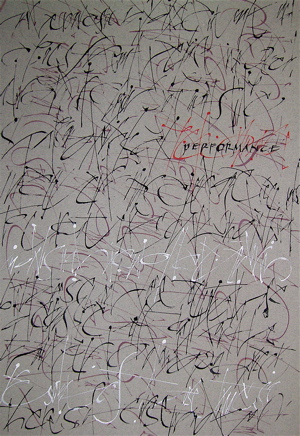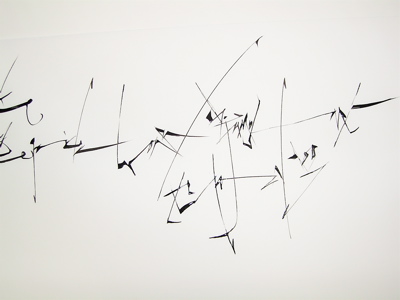
ポリリズミック
先週末に来日中のデニス(デニオとも言う)ブラウン氏のワークショップを受講しました。
タイトルは「ポリリズミック」!
いくつものリズムが入っている文字を求めて今日も書く、明日も書く、あさっても書くのです。
右脳と左脳から出た信号が手に流れて、自然と美しい文字や線が即興的に直感的に生まれてくる様に、ひたすら書く。ペンを意識的に「コントロール」するのではないのです。Let them go!
あんなラインできないわ〜、デニ男じゃないからムリ〜、と逃げるのは簡単です。・・・が、ここであきらめてはいけまへん。あきらめたら女がすたるっ!?
だって、あきらめたらこれより先にはいつまでたっても進めないし、進めたらもっと先が見えて来るかもしれないのです〜。あ〜、でも大変!
そういう気持ちにさせるデニ男さんはやはり一流のカリグラファーなんですね。いやはや、すごいザンス!
ワタシ的にはとっても受けました。
Sさんのポリリズム、ステキですー。スキスキっ。
興奮していますっ。私ー。
今回のWSではベテラン様揃いなので、イタリック以外のものも期待していました。すばらしいです!!!
書けば書くほど燃えてきますよね。私も燃えています。。デニ男は「デニオ」という響き、好きみたいです。
確かに、本当にその気になっている私、彼の才能、パワーのおかげです。やっぱりすごいですね。
ikukoさんのポリリズミックも是非是非発展させて、いつか必ず拝見させて下さいね。楽しみにしていますっ!燃えてくださいっ!
ゴッちゃんにディアンコ、そして”デニ男”だなんて、カリグラフィー界の巨匠達がとても身近に感じられちゃう〜。ポリリズミック、皆さんが体ごと神経を集中して描いている姿が目に浮かびます。凄そうです。皆さんの進化していくモジ達を拝見するのを楽しみにしています!